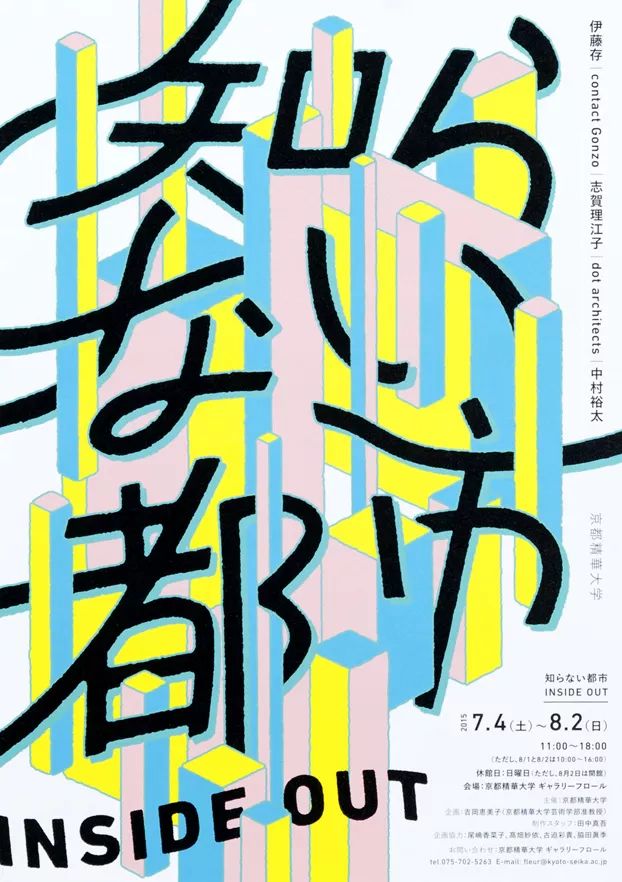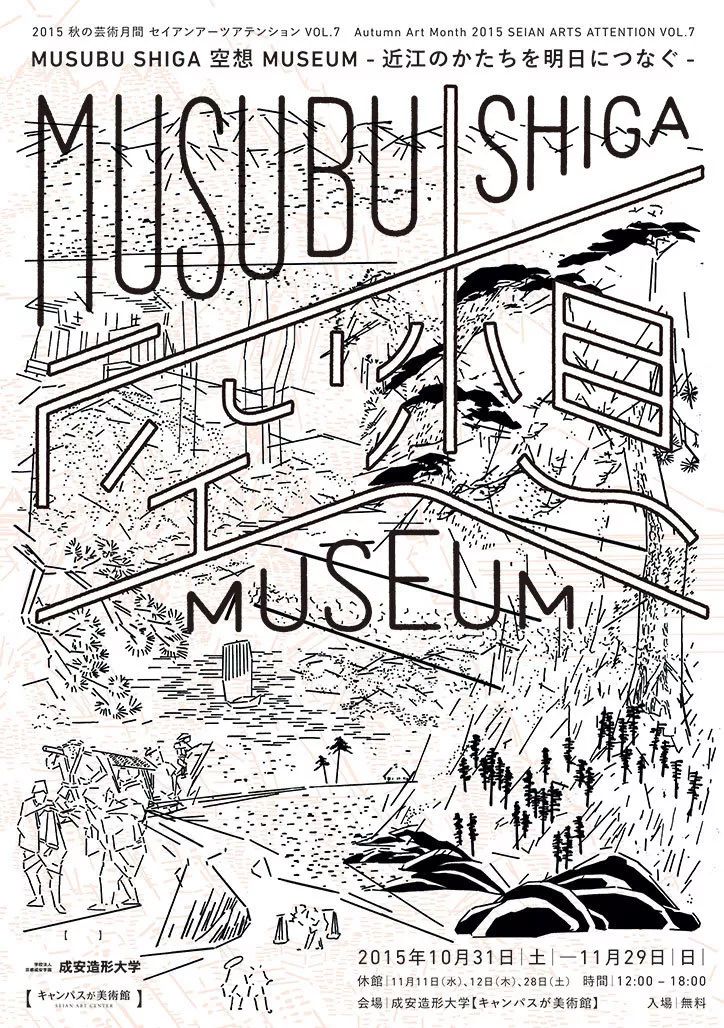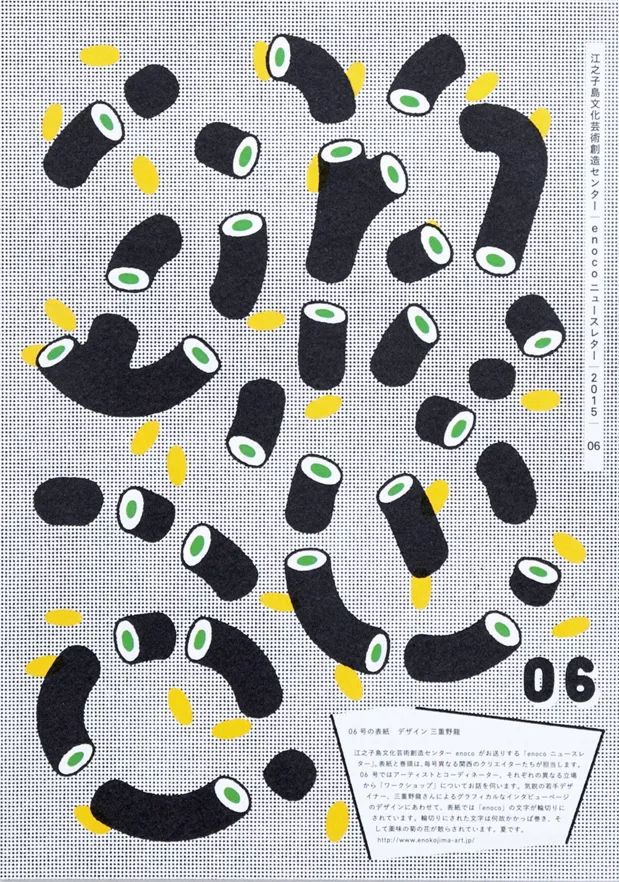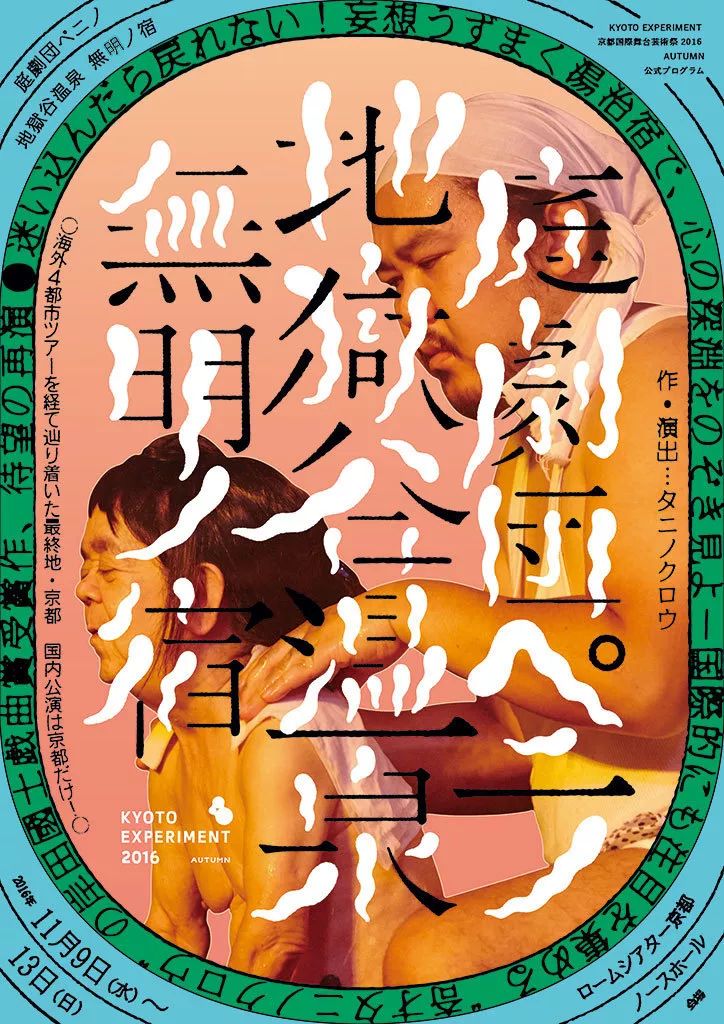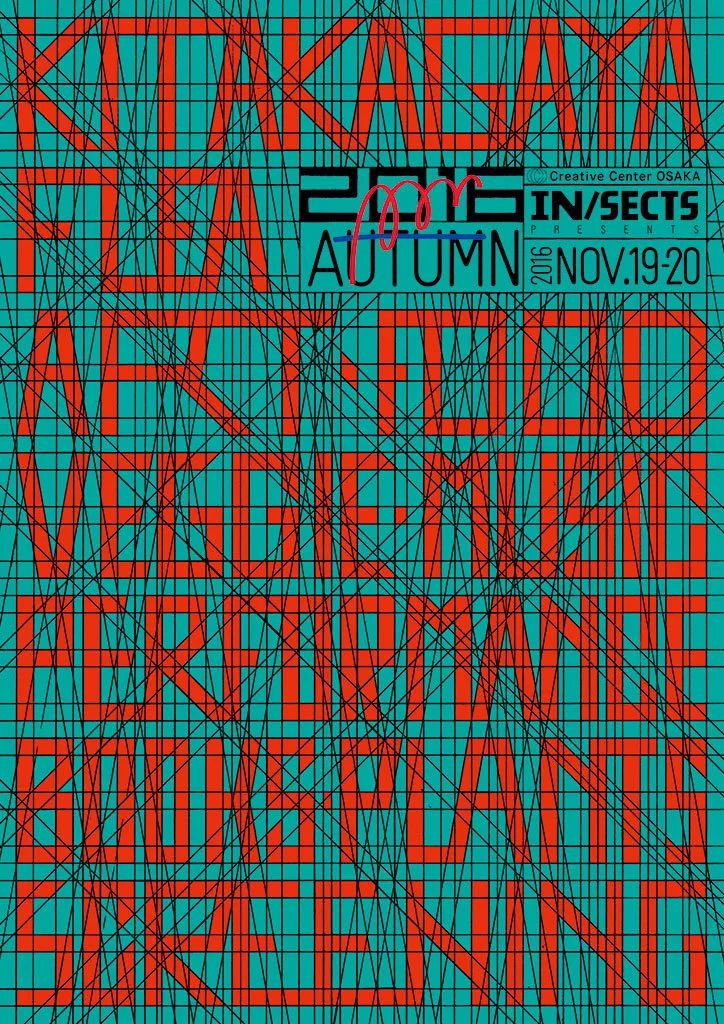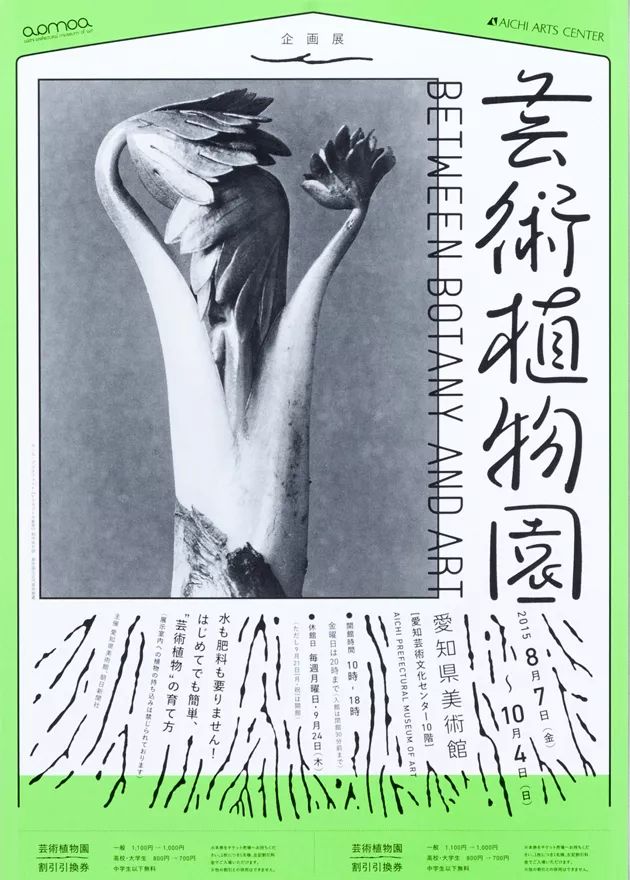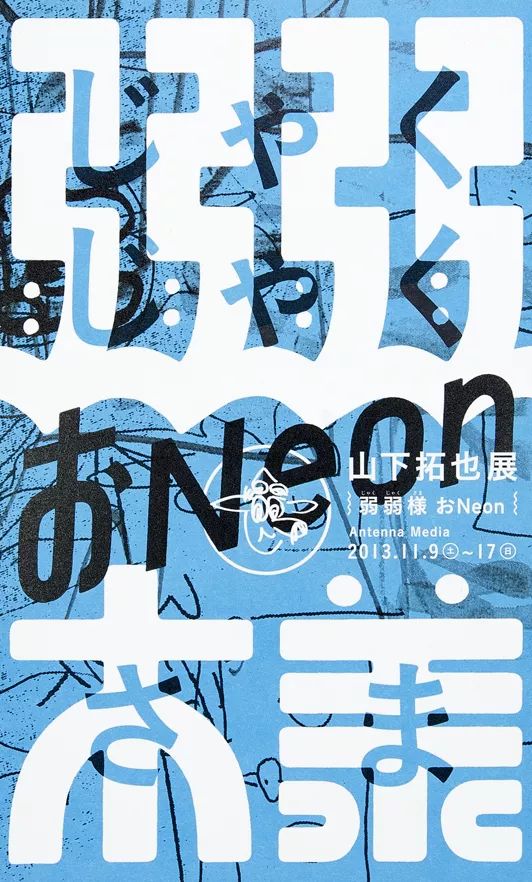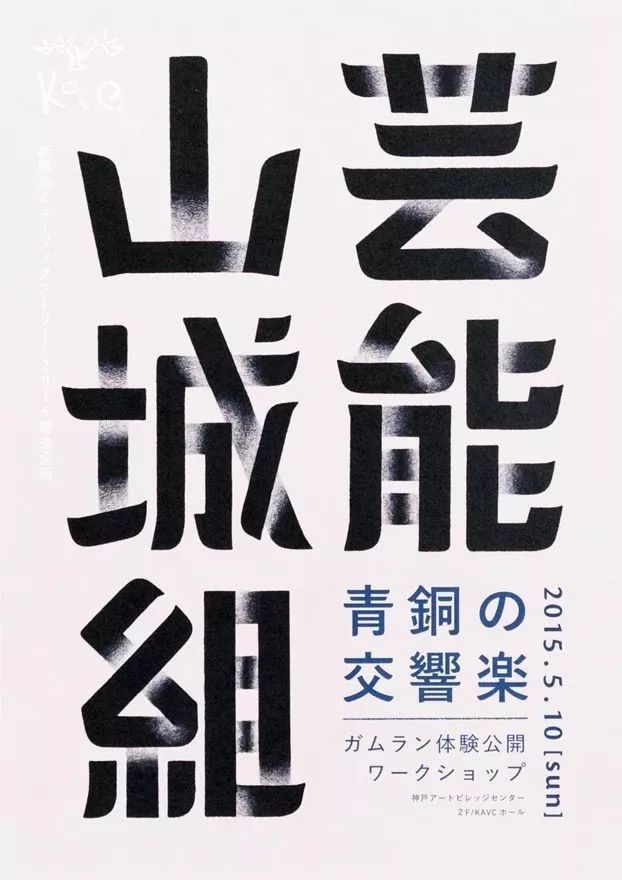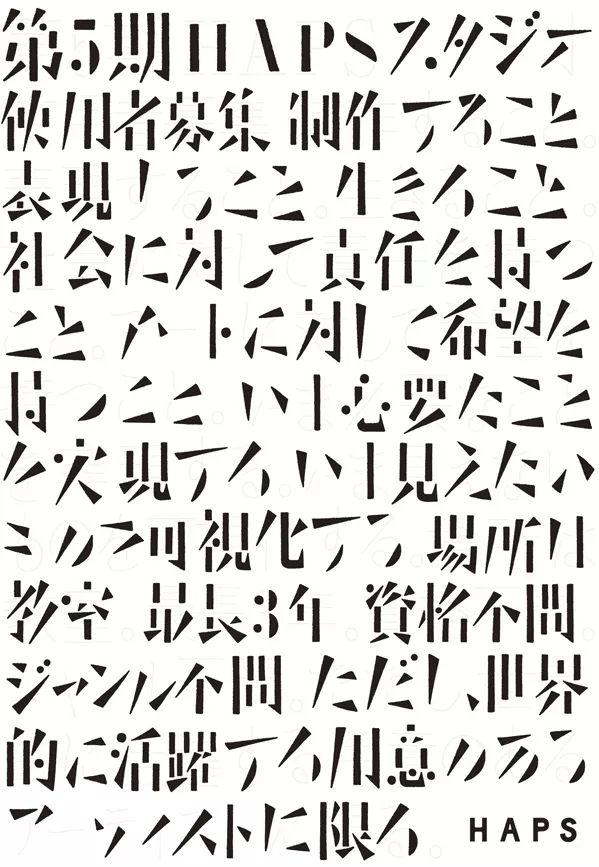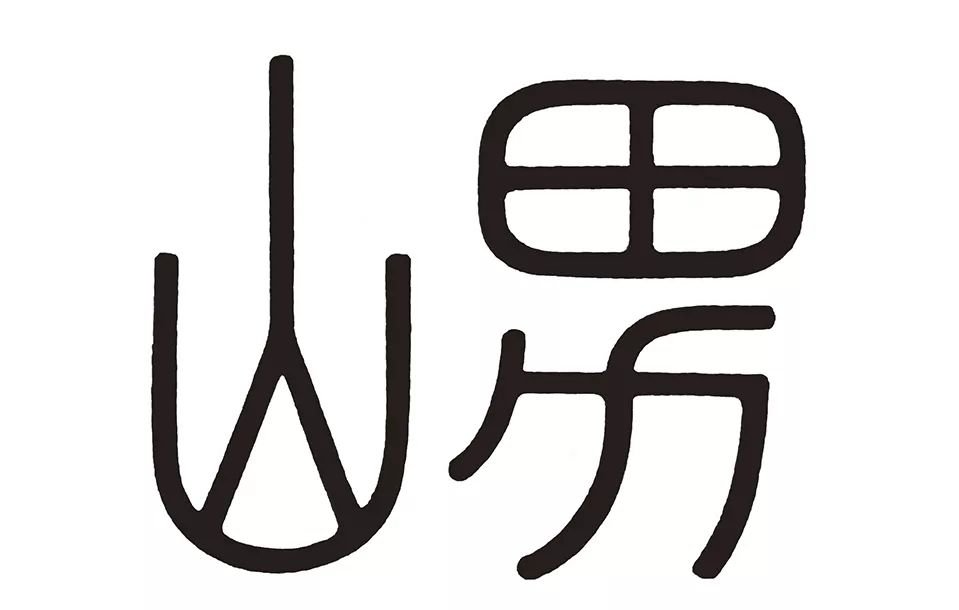
令人印象深刻的文字设计是什么样的?
日本的字体设计在设计圈向来是享誉盛名的。在日本,有许多专业从事字库设计的工作室和个体机构,日本设计师对于字体造型的研究和实验遍布在各个领域中,其中尤以运用在海报、企业视觉识别系统、书籍装帧设计上最为常见。今天我们要为大家介绍的是一名来自日本的平面设计师——三重野龙,其字体设计风格以富有辨识度和活力而广受人们的喜爱。那么,什么样的字体能让人产生深刻的印象呢?日本平面设计师三重野龙(Mieno Ryu)出生于1988年,2011年从日本私立大学——京都精华大学的平面设计系毕业,同年开始了自己自由设计师的道路。
在三重野龙的作品中,无论是给画廊、商店、电影作品设计的海报还是标志设计,随处可见暴走一般的字体,充满了能量,很能体现出作品的语义和设计师的个性。他对排版和字体的大胆运用显示了他对构图的自信,最终呈现出活力十足的作品。他的作品大多数是为艺廊和展览所创作,同时也有许多以字体为主体的识别设计。三重野龙的海报设计构成简洁有力、主题清晰,同时又具备层次与细节,人文风格强烈。虽然他的作品多为展览的宣传制作物,延伸性较少,但因产量丰富,也累积了丰富多元的表现,令人印象深刻。
在他创作的项目中,其中一个是为日本铁路艺术节做的海报设计,三重野龙从另一个角度为我们展示了火车站的形象,在海报中结合了摄影和大量的文字。这种不规则的布局代表了嘈杂的火车站的环境。
另一个项目——声音表演,是为一个音乐节而设计的,目的是为了表现这个活动所传达的精神。三重野龙希望通过视觉来想象音乐和人之间的身体互动。三重野龙说,他的创作灵感来自于对自然形态和形状的观察——树叶的纹理、木纹、鱼的皮肤纹路,他把它们转换成符号和印刷字体,因为他喜欢自然和艺术之间的交流。三重野龙在大学期间花了很长的一段时间学习绘画,当他毕业的时候,却对自己设计的作品并不见得有多满意,甚至都不敢去找工作。后来他选择在京都做一些兼职的工作,直到大学的一位老师和他取得了联系,让他帮忙做一些博物馆的视觉设计。三重野龙接到的第一个项目是为京都漫画博物馆举办的赤塚不二夫(Fujio Akatsuka)作品展览做视觉形象。现在回想起来,如果错过了那个项目,那可能会失去许多宝贵的设计经验,因为该项目不仅仅只是需要他去制作宣传单,还要为展览设计许多视觉上的内容。与使用现有字体相比,三重野龙似乎更喜欢创建新字体,那是因为他很肯定自己想亲身参与设计过程,想用手写字来开始对文字的创作。三重野龙的作品多为艺术展览的海报设计,利用阴影的效果,让字体跳脱出平面海报,立刻抓住众人的眼睛!
三重野龙经常喜欢让文字变形,他常利用线条的弯曲融入整体海报中,将日文字体延伸,流畅阅读的同时也产生出美丽的图像,具有强烈的艺术性。除了海报的设计之外,三重野龙也有许多字体设计的作品,各种类型的表现方式,无论是图文合一、插画的型态、或是单纯字体设计,也都有强烈日本设计的味道。